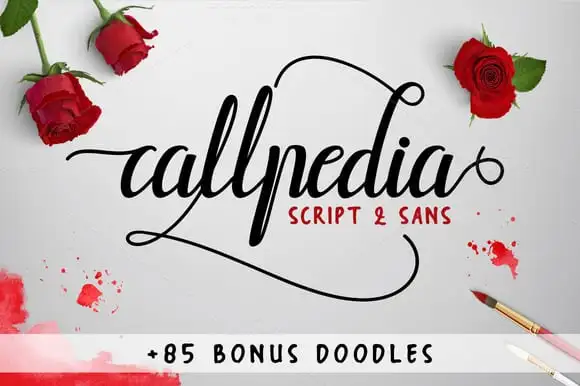
Callpedia Script Font – Fonte Grátis
Callpedia Script Font
A Callpedia Script Font é uma criação inovadora criada pelo designer Apon Bahrainy para facilitar a criação de projetos de design gráfico que necessitam de letra perfeita e tipografia elegante. Com dois estilos exclusivos, essa fonte oferece um total de 949 caracteres script e 202 caracteres sans-serif, garantindo uma variedade suficiente para atender às diferentes necessidades do seu trabalho. Ideal tanto para projetos digitais como impressos, a Callpedia Script é perfeitamente adequada para variados usos, incluindo logotipos, assinaturas de carta, estandartes, etiquetas, materiais de marca e até mesmo cartazes e selos. Sua versatilidade é imensa, fazendo-a uma escolha ideal tanto para projetos pessoais quanto comerciais. Se você deseja usar a Callpedia Script Font em um projeto que não seja de uso pessoal, o criador oferece facilidades para adquirir licenças com segurança no link fornecido: https://creativemarket.com/aponjohn/712448-Callpedia-2-Styles-Bonus. Seja você um designer gráfico profissional ou iniciante, a Callpedia Script é uma fonte indispensável para sua coleção de recursos gráficos.